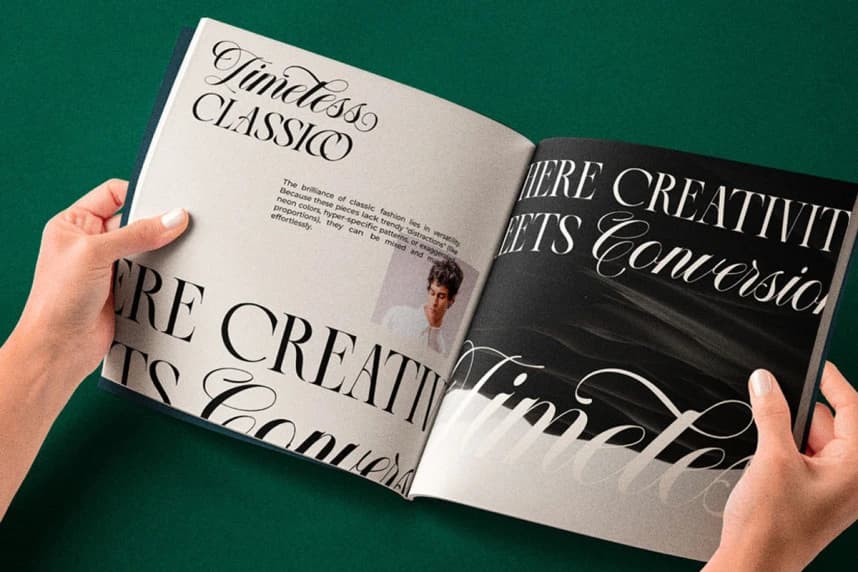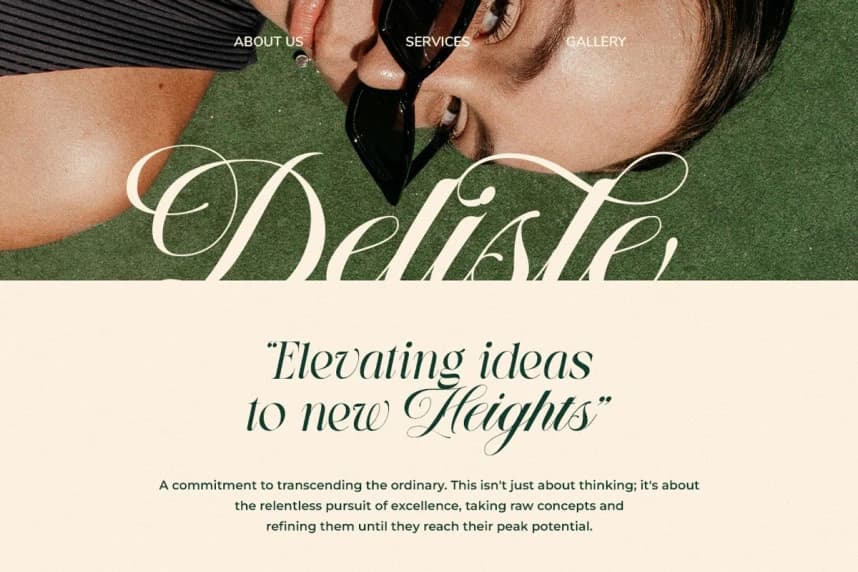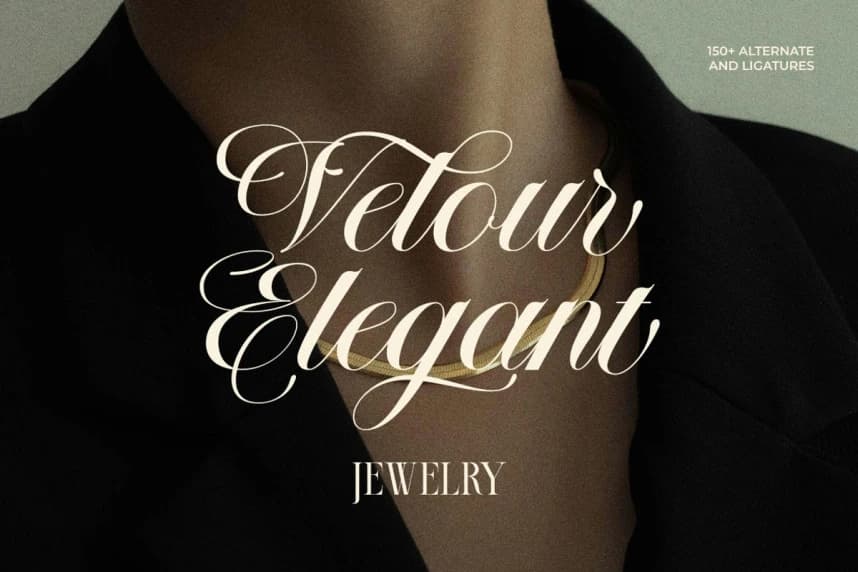
LT The Heistha Editoryal Font Çifti
LT The Heistha Editorial Font Duo, zamansız zarafeti simgeleyen çarpıcı bir font ikilisi. İnce, modern bir serif yazı tipini geniş ve zarif bir script ile kusursuz bir uyum içinde bir araya getirerek, bu koleksiyon çalışmalarınıza premium bir dokunuş katmak için titizlikle tasarlandı.
LT The Heistha Editorial Font Duo, zamansız zarafeti simgeleyen etkileyici bir yazı tipi ikilisi. İnce, modern bir serif yazı tipini geniş, zarif bir el yazısına kusursuz bir biçimde eşleştirerek, bu koleksiyon çalışmanıza premium bir dokunuş katmak için titizlikle tasarlandı.